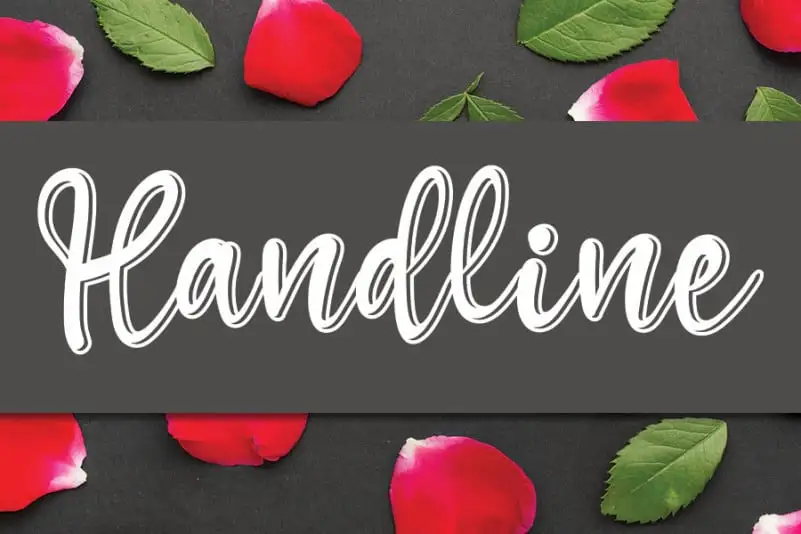
Handline Display Font – Download Grátis
A fonte ‘Handline Display Font’ é uma escolha ideal para criar designs chamativos e diferentes, que destacam-se no seu ambiente. Seu design levemente desenhado dá um toque sofisticado a qualquer projeto visual sem perder a facilidade de uso. Ideal para headlines e materiais impressos em grandes tamanhos, essa fonte traz uma personalização única ao seu trabalho, tornando sua marca ainda mais destaca. Com sua tipografia elegante e legível, a ‘Handline Display Font’ é perfeita tanto para criações digitais quanto para material impreso de alto nível. Sua simplicidade no design faz dela um ótimo complemento para qualquer tipo de projeto visual, garantindo que o seu texto brilhe na tela ou nas páginas dos jornais.